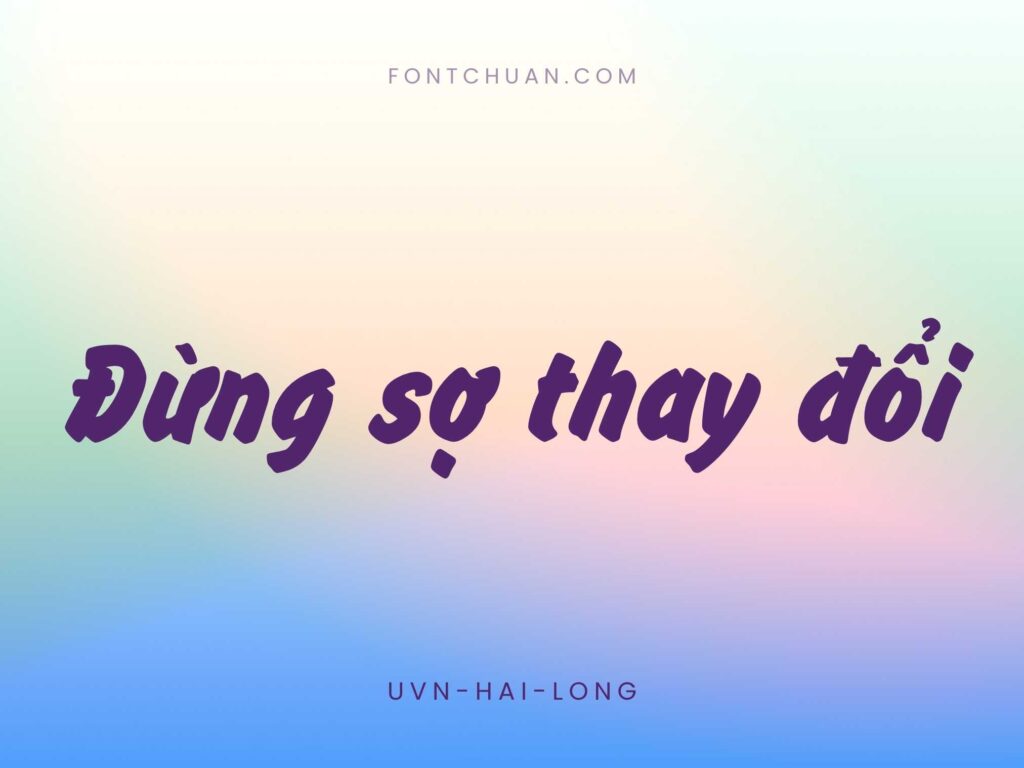
Font UVN Hai Long Việt Hóa
UVN Hải Long là một phông chữ thư pháp mang phong cách nghệ thuật viết tay truyền thống. Được thiết kế với các nét bút lông mềm mại và uyển chuyển, phông chữ này tạo nên sự thanh thoát và tinh tế cho các tác phẩm thiết kế. UVN Hải Long hỗ trợ đầy đủ các ký tự tiếng Việt, giúp người dùng dễ dàng sử dụng trong các dự án sáng tạo liên quan đến văn hóa Việt Nam.
Với thiết kế độc đáo và nghệ thuật, UVN Hải Long phù hợp cho các ứng dụng như thiệp mời, tiêu đề sách, thiết kế logo và các ấn phẩm nghệ thuật. Trong lĩnh vực sự kiện, phông chữ này có thể được sử dụng trong các dịp như lễ hội, lễ cưới và các sự kiện văn hóa. Ngoài ra, UVN Hải Long còn có thể được ứng dụng như một Font chữ ảnh cưới, mang đến sự tinh tế, lãng mạn và sang trọng cho các album, thiệp cưới hoặc các sản phẩm kỷ niệm đặc biệt. Ngoài ra, font cũng thích hợp cho các ngành nghề như thiết kế đồ họa, nghệ thuật trang trí và xuất bản.